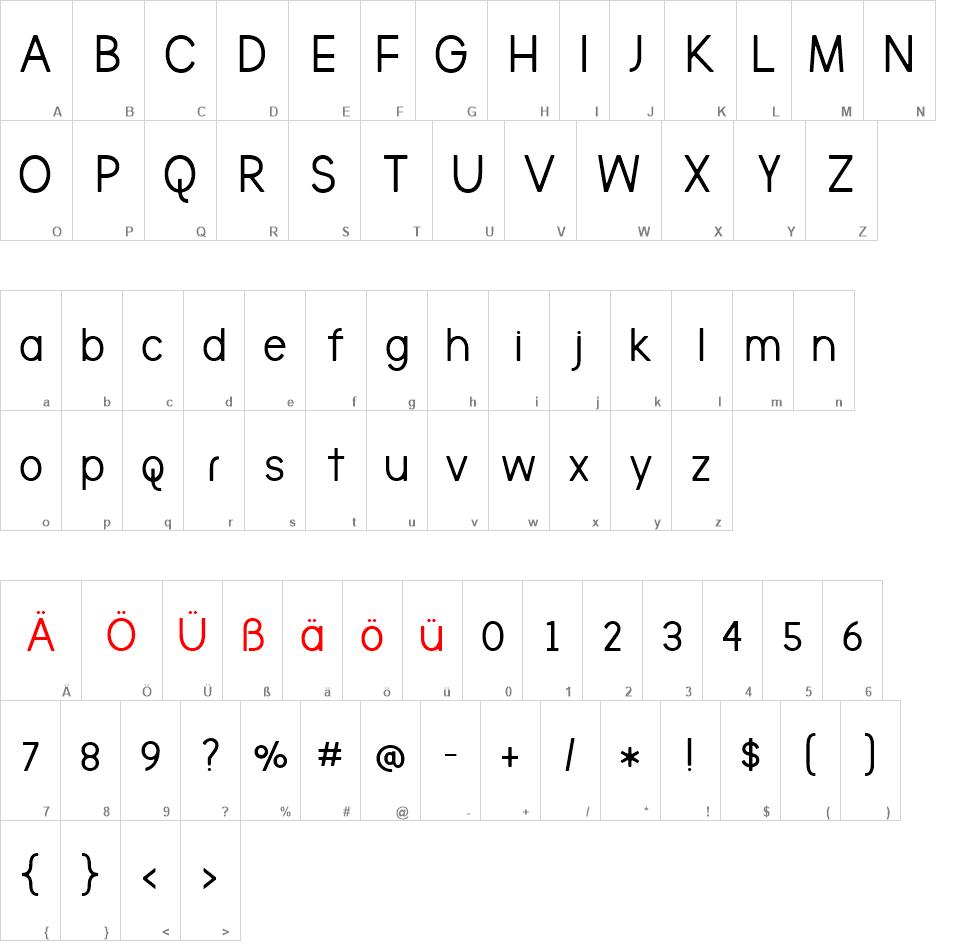
The Brooklyn Smooth
Das Brooklyn Smooth-Paar eignet sich hervorragend für Skriptschriften und eignet sich gut für Bylines und Text. Die Schriften haben jeweils mehr als 400 Zeichen, einschließlich kyrillischer und viel lateinischer Akzente.